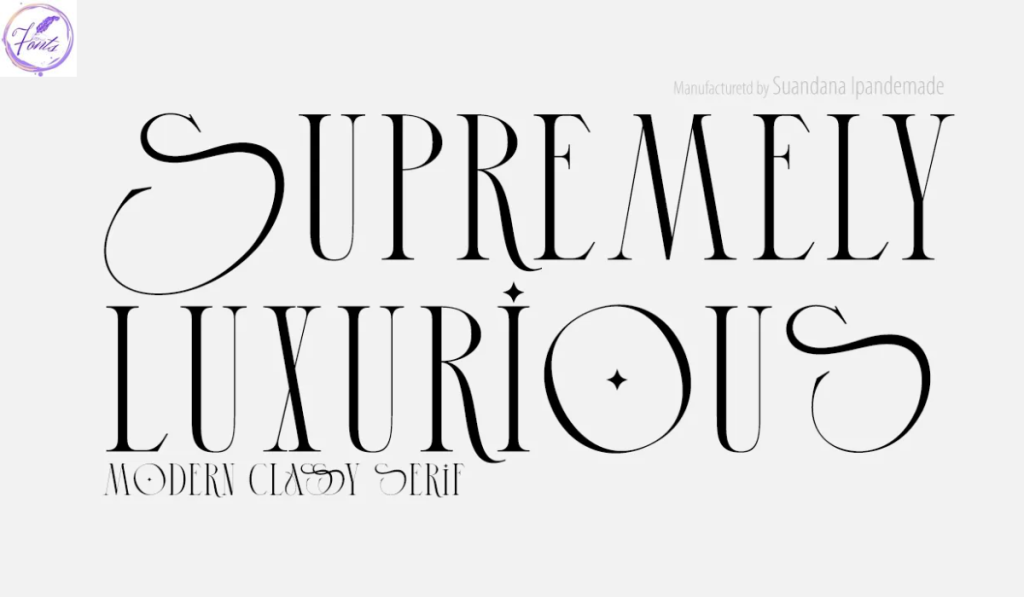
Font chữ Luxury Supremely việt hóa
Tác giả: Maulana Azwar
Ngày phát hành: 2019
Ngôn ngữ: Tiếng Việt, nhiều ngôn ngữ khác
Bộ Font: Supremely Luxurious
Phân loại: Cá tính, độc đáo
Kiểu chữ: Có chân
Độ dày: Regular, Italic
Nếu bạn đang tìm kiếm một font chữ sang trọng, đẳng cấp và độc đáo cho các dự án thiết kế của mình, font chữ luxury supremely chính là sự lựa chọn hoàn hảo dành cho bạn. Font chữ này được thiết kế bởi nhà thiết kế nổi tiếng Maulana Azwar vào năm 2019, với phong cách hiện đại, tinh tế và đầy sức hút. Luxury supremely mang đến một cảm giác sang trọng, quyền lực và thu hút mọi ánh nhìn ngay từ cái nhìn đầu tiên.
Đánh giá font chữ luxury supremely
Font chữ luxury supremely không chỉ đẹp mắt mà còn rất dễ đọc và dễ sử dụng. Các ký tự trong bộ font này được thiết kế tỉ mỉ, với các đường nét mềm mại, uốn lượn tạo nên sự hài hòa và cân đối. Bộ font bao gồm đầy đủ các ký tự chữ cái, chữ số, dấu câu và ký tự đặc biệt, giúp bạn dễ dàng sáng tạo và thể hiện ý tưởng của mình. Luxury supremely phù hợp với nhiều phong cách thiết kế khác nhau, từ thiệp cưới, logo, bao bì sản phẩm cho đến các ấn phẩm quảng cáo cao cấp.